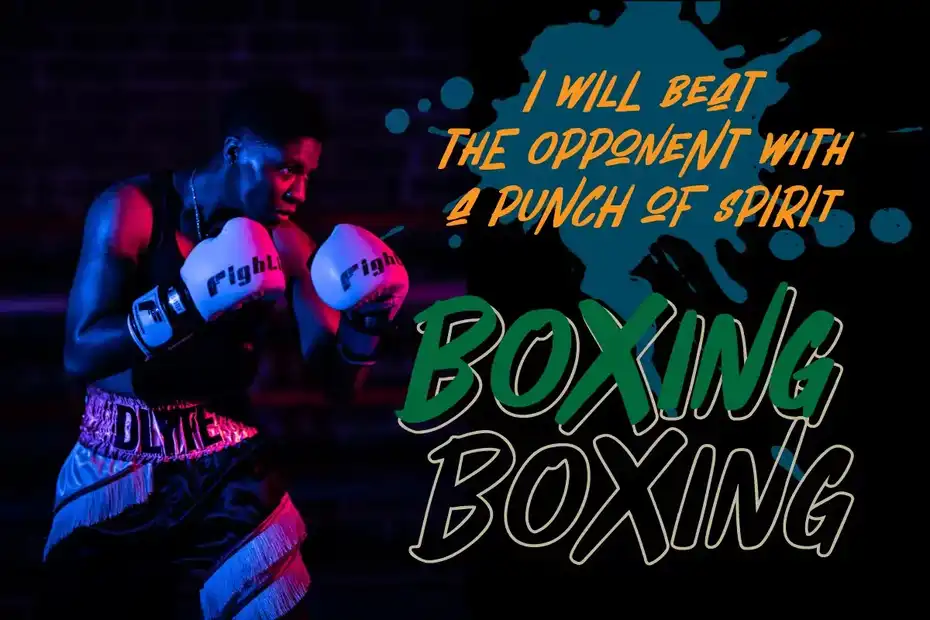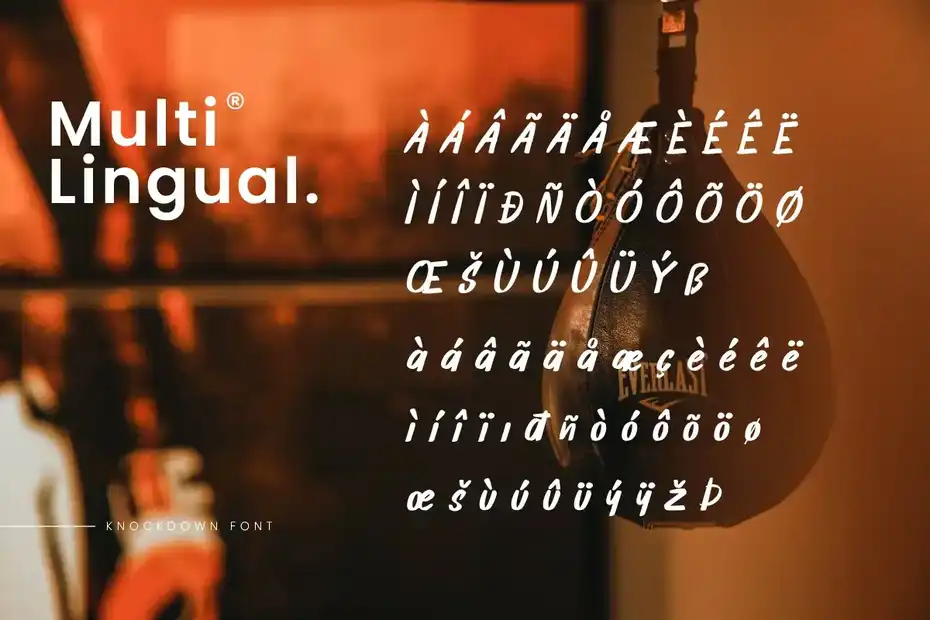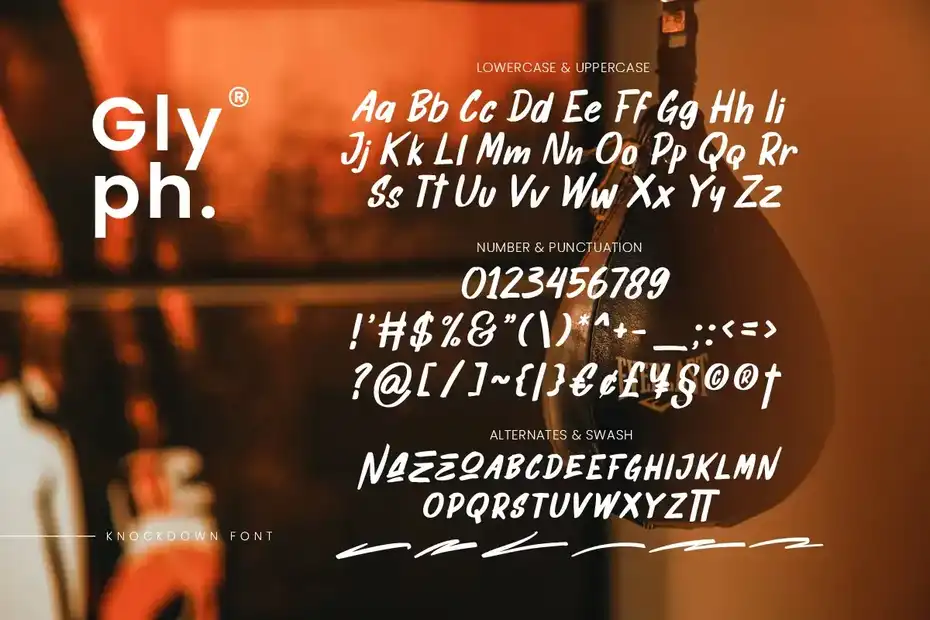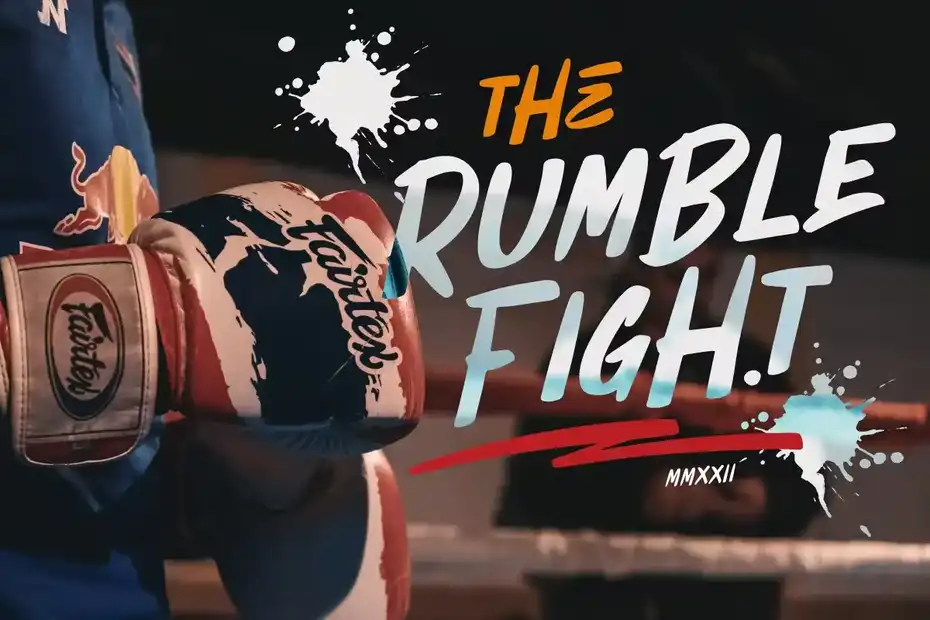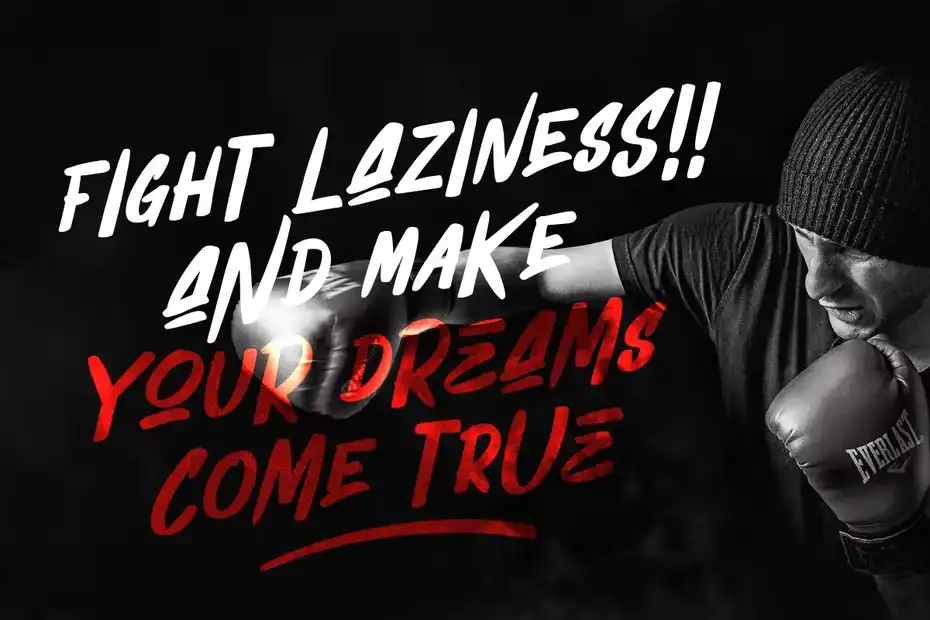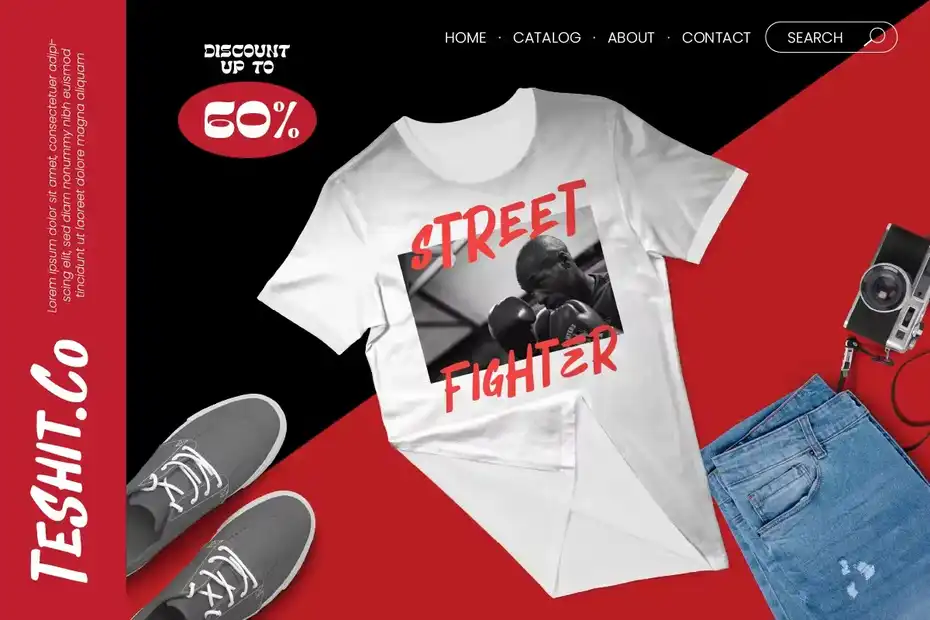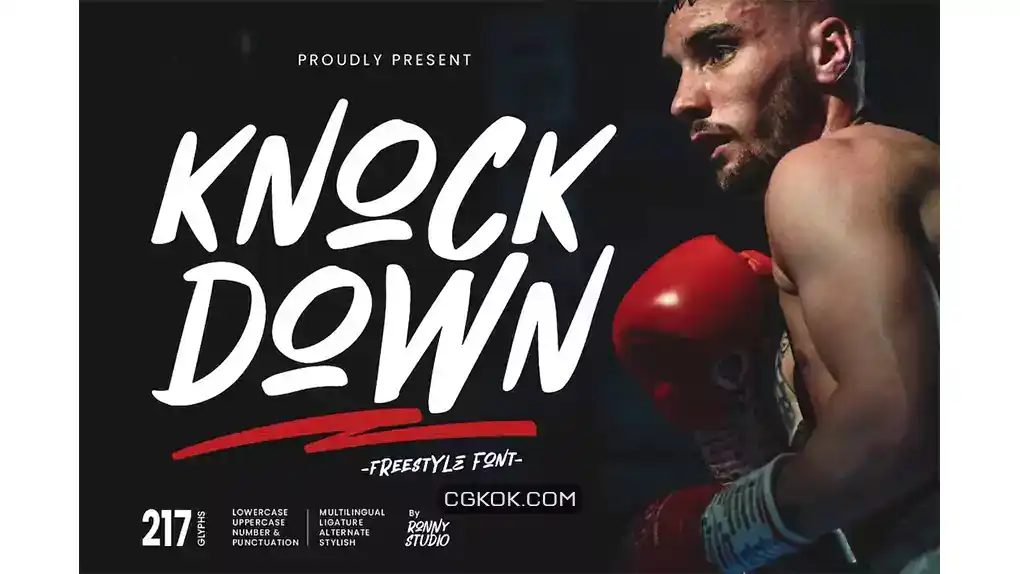
دانلود فونت انگلیسی دست نویس Knock Down – Handwritten Freestyle Font
فونت انگلیسی دست نویس Knock Down : این مجموعه شامل یک فونت دست نویس است که برای لوگو، نقل قول، محصولات، تیشرت ها، بسته بندی، کمیک ها، مجلات، پوستر ها، رویداد ها، پست شبکه های اجتماعی، کتاب ها و پوشش متنی بر روی تصویر پس زمینه مناسب میباشد.